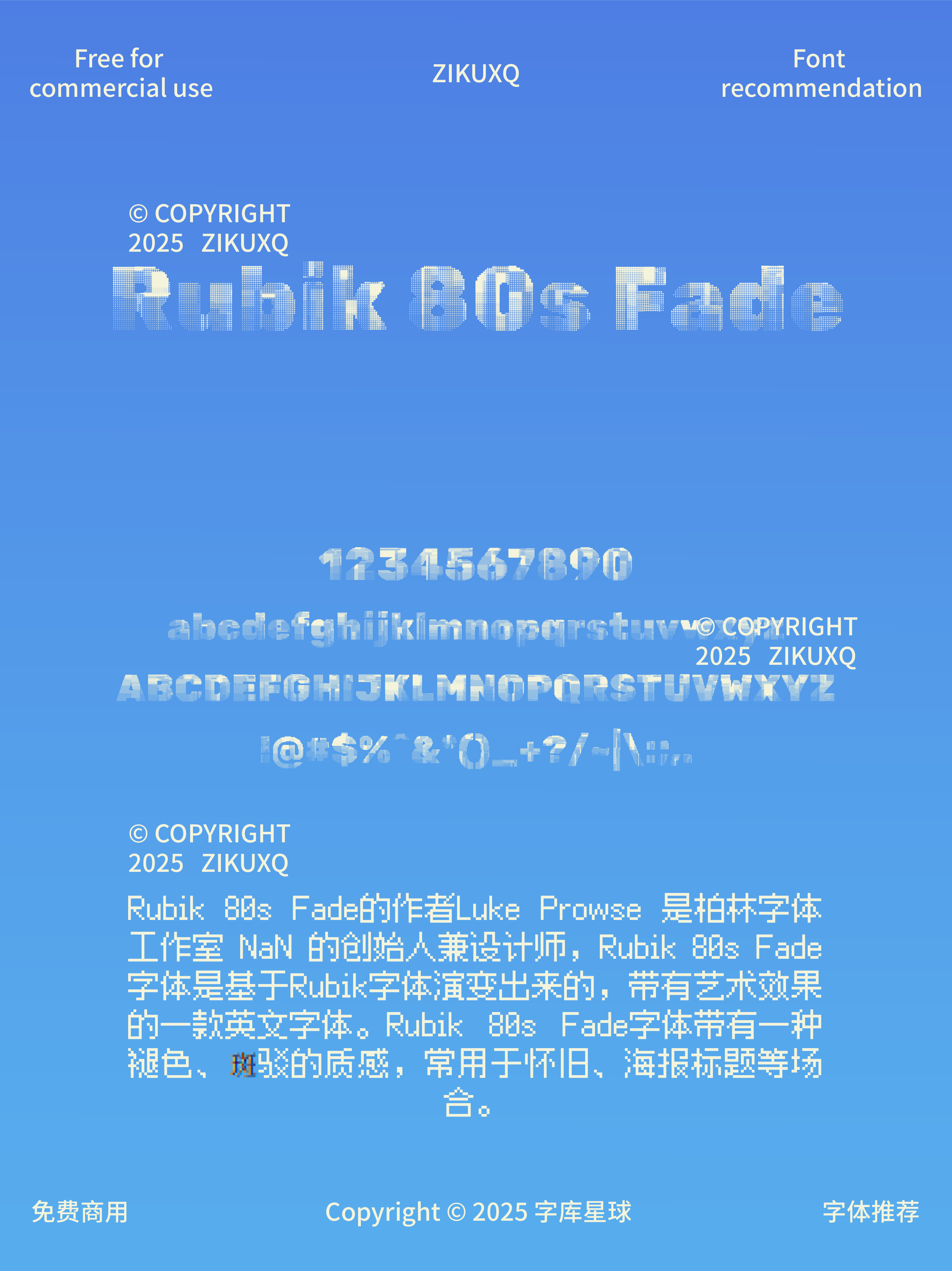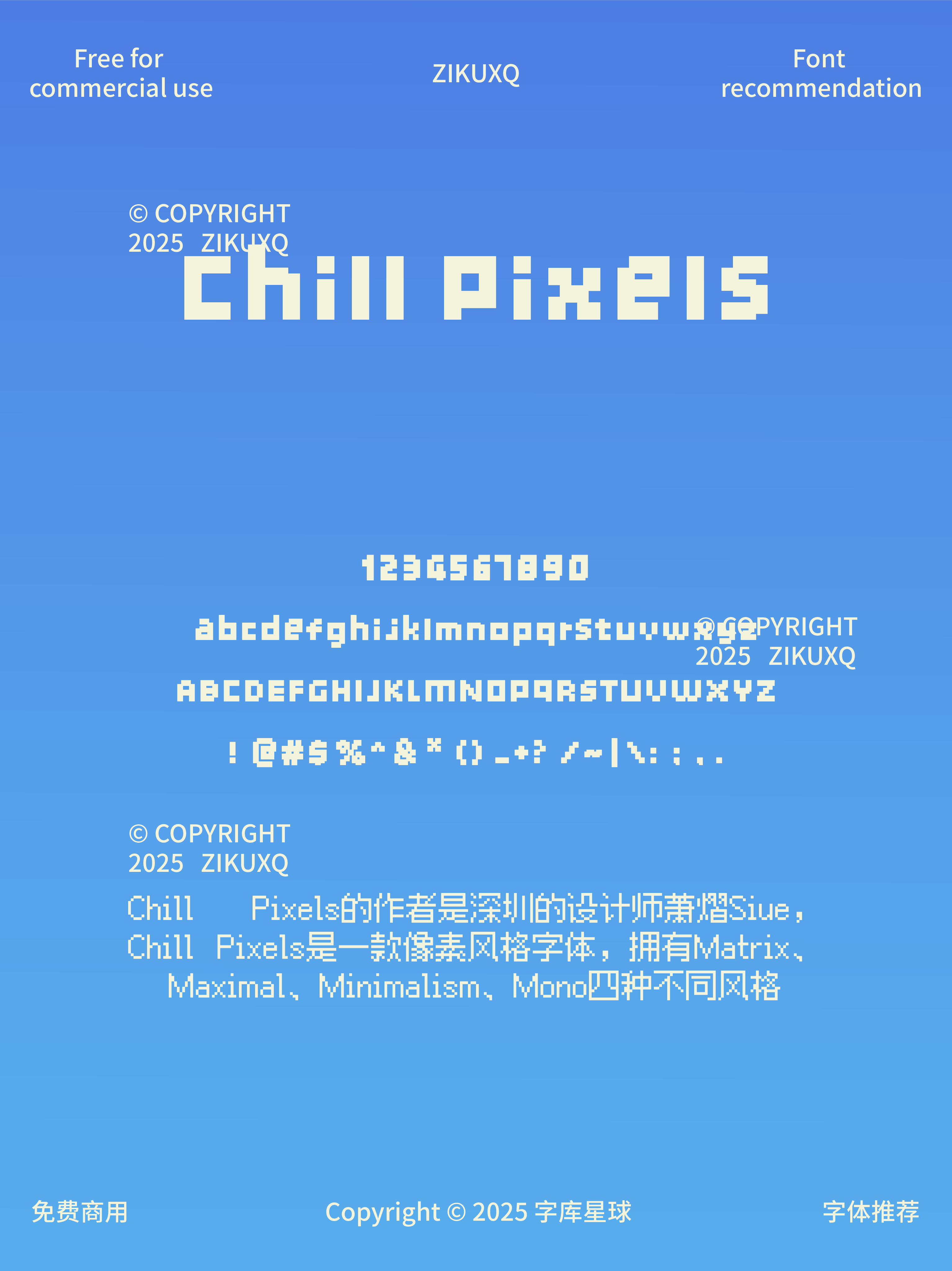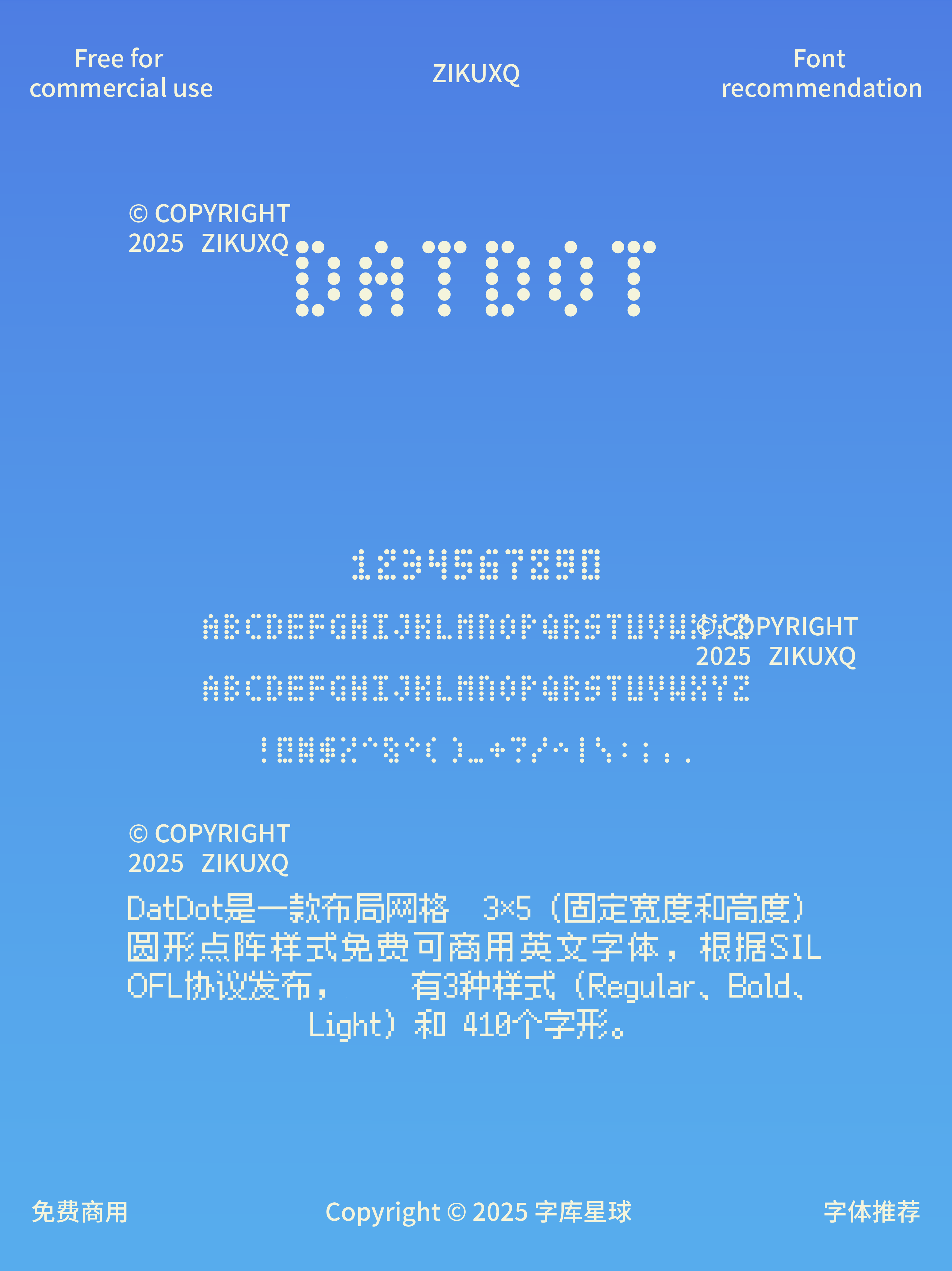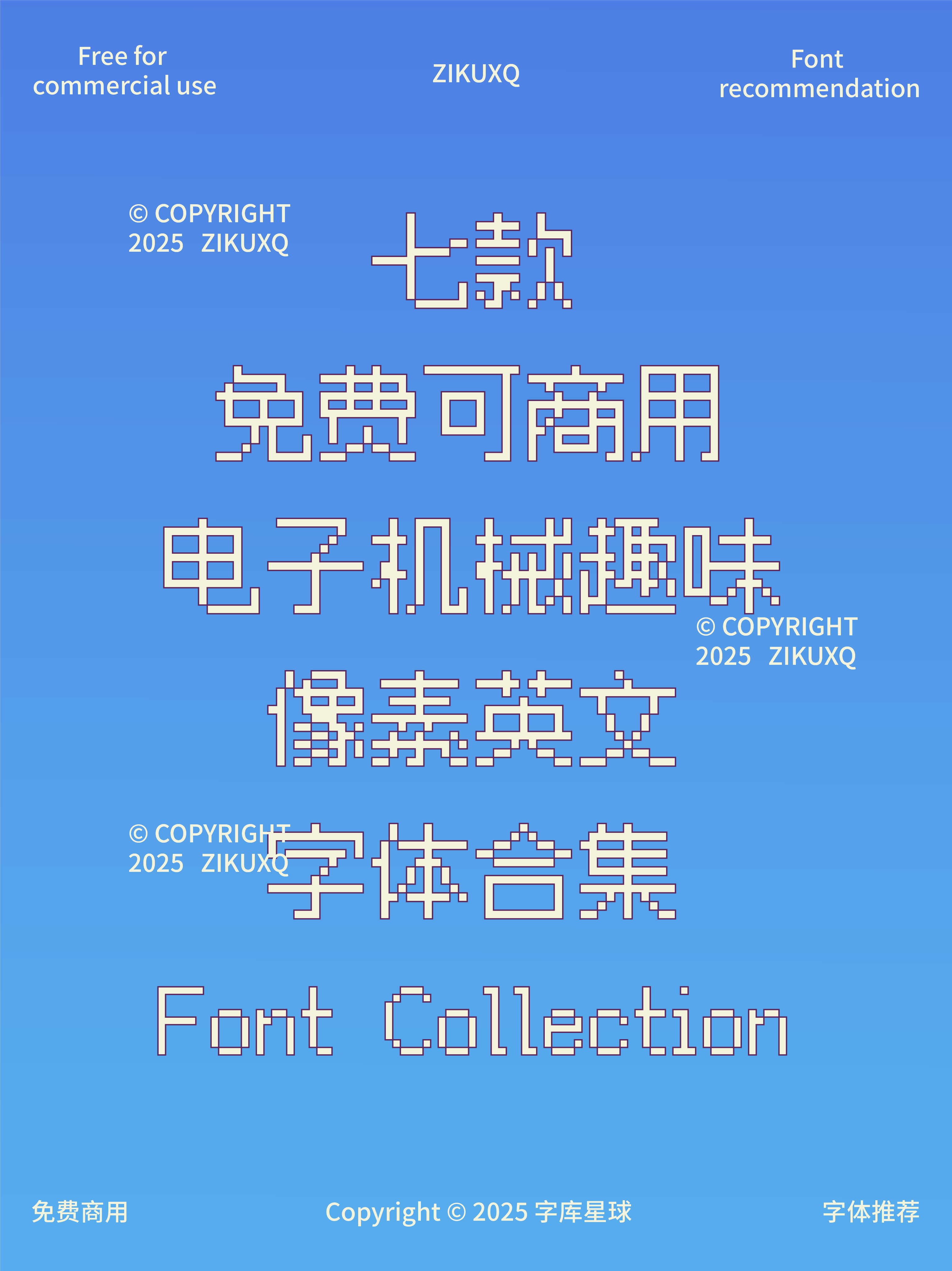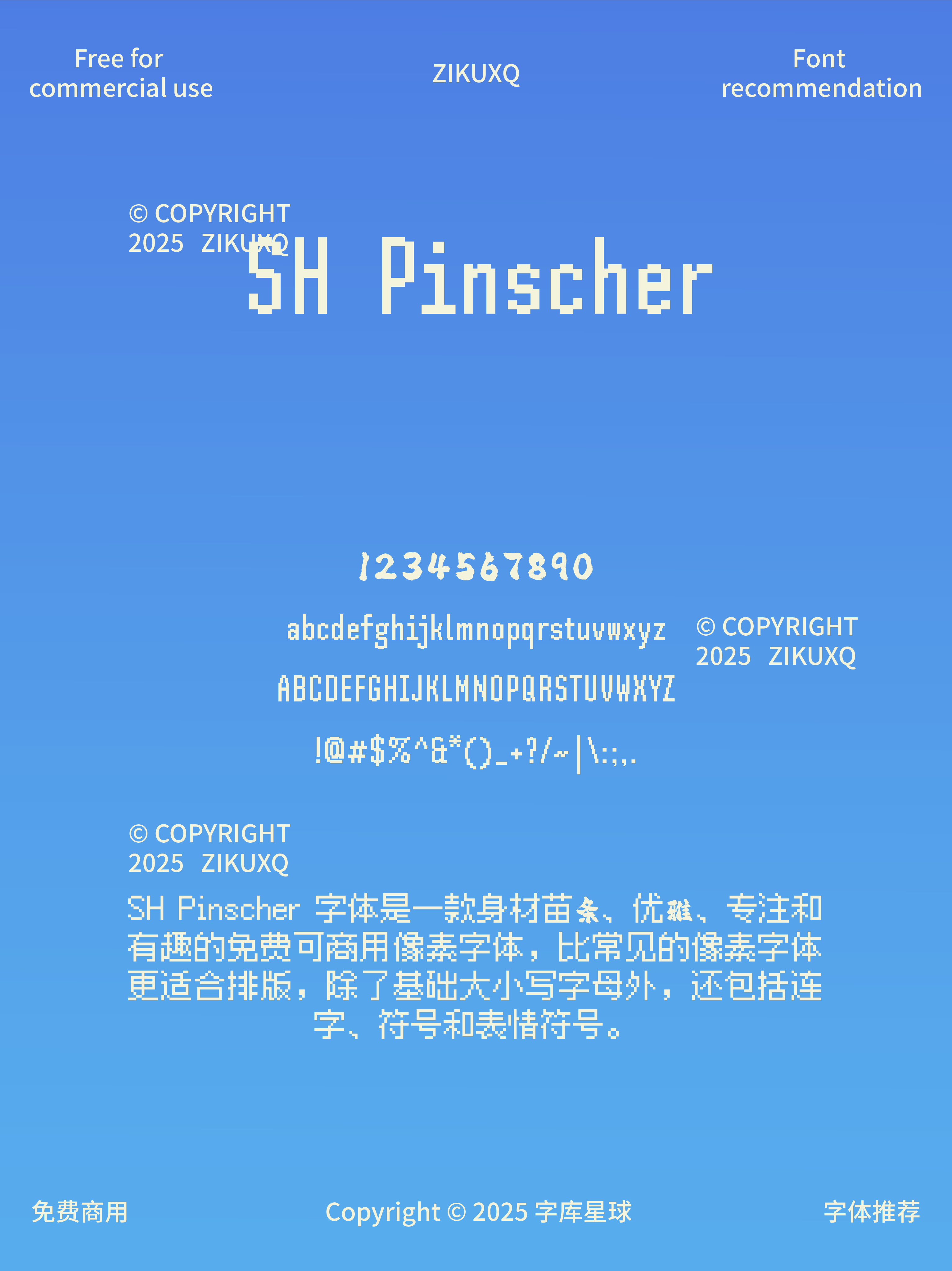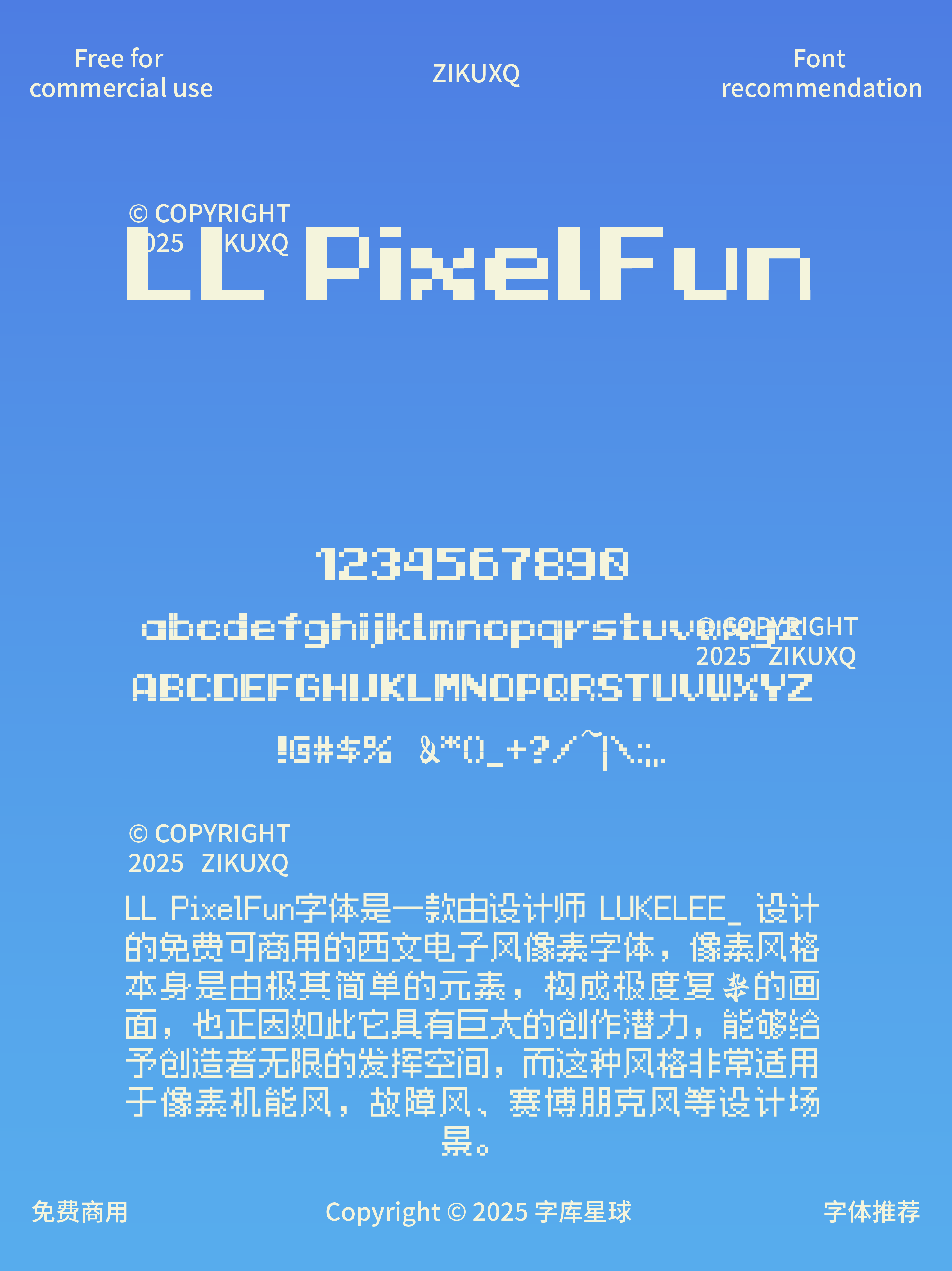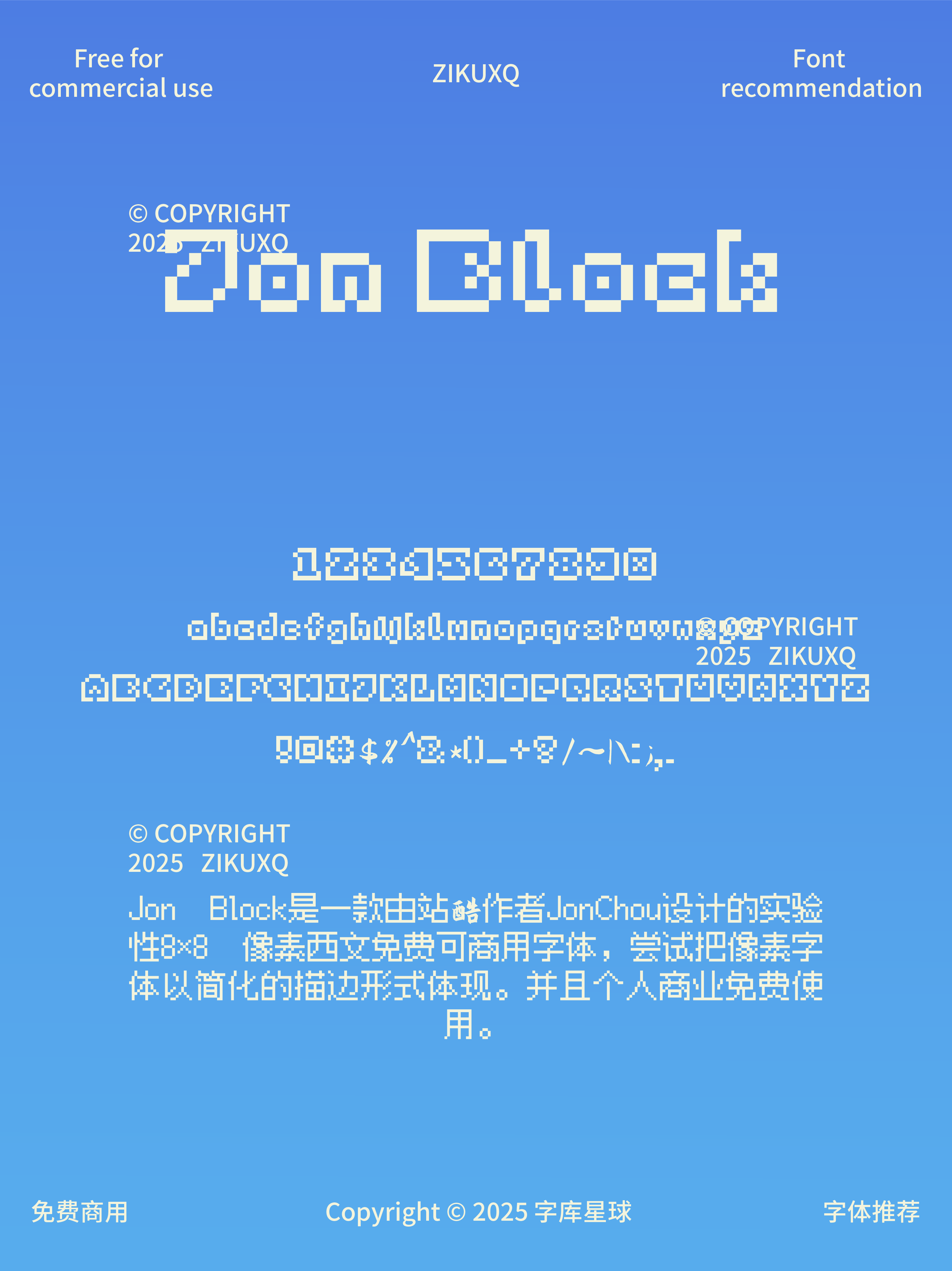
七款免费可商用电子机械趣味像素英文字体
今天给大家分享七款超酷的免费可商用电子机械趣味像素英文字体,轻松为你的设计增添独特魅力~
常用于游戏的像素字体,视觉效果清晰锐利,能完美融入电子游戏氛围。支持多种语言,包括拉丁文、希腊文及符号等,适用范围广。
专为本地化像素艺术游戏设计的位图字体,方正刚直的字形让人想起经典电子游戏,在游戏标题、海报设计中能迅速吸引眼球。